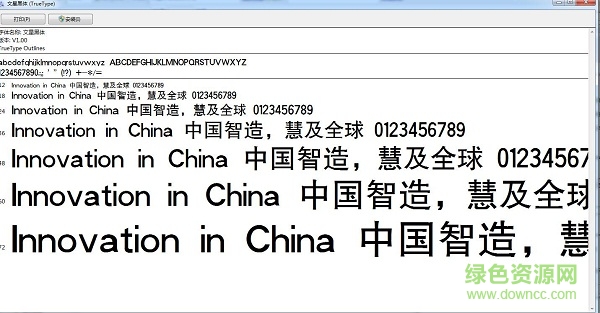
文星黑體字體
文星黑體字體是一款打包好的無(wú)襯線字體,字面干凈,粗細(xì)一致,非常地清晰易讀,具有良好的顯示效果,適用于電子屏幕、網(wǎng)頁(yè)設(shè)計(jì)、書籍期刊等領(lǐng)域,歡迎大家免費(fèi)下載!
黑體字體介紹
“黑體”是一類字體的總稱,有很多字體都屬于這個(gè)范疇,黑體是在現(xiàn)代印刷術(shù)傳入東方後依據(jù)西文無(wú)襯線體所創(chuàng)造的。所以黑體這個(gè)詞的范疇和無(wú)襯線字體是類似的。而宋體就可以被稱作襯線字體。